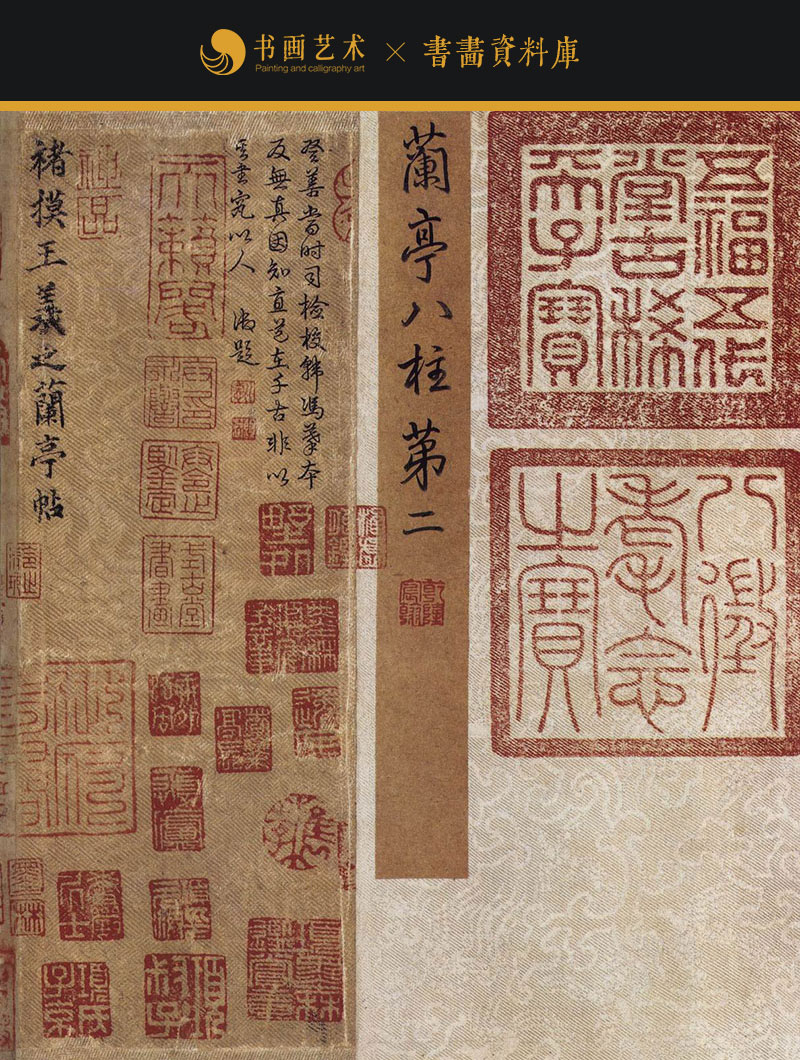
褚遂良是唐朝的书法家,他在书坛的影响力很大,与欧阳询、虞世南、薛稷合称初唐四大家。在书法的临摹上,不仅要临摹其形,也要临其神韵。在这点上褚遂良做到了形神兼备,不仅掌握了王羲之的笔法,对于书圣的神韵也有着深刻的理解。同样是临摹《兰亭序》,冯承素在临摹的时候力求接近原帖,在用笔上有着王羲之飘逸之感,在起笔和收笔上达到高度相同的境界,在章法布局上也遵循着王羲之的法度,但是褚遂良所临摹的版本和冯承素又有一点区别。